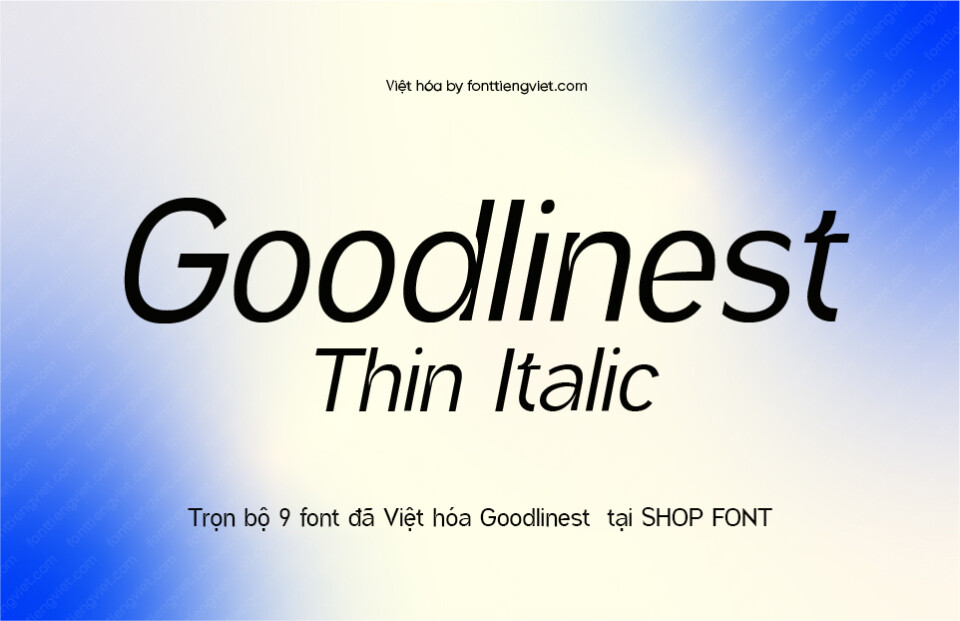
Font Việt hóa 1FTV VIP Goodlinest Thin Italic
Font Việt hóa 1FTV VIP Goodlinest Thin Italic: Đẳng cấp thiết kế thanh lịch và hiện đại
Giới thiệu về Font Việt hóa 1FTV VIP Goodlinest Thin Italic
Trong thế giới sáng tạo đồ họa ngày nay, việc lựa chọn bộ Font Miễn Phí chất lượng đóng vai trò then chốt giúp sản phẩm truyền thông trở nên chuyên nghiệp hơn. Font Việt hóa 1FTV VIP Goodlinest Thin Italic là một trong những đại diện tiêu biểu cho phong cách tinh tế và nhẹ nhàng. Đây là phiên bản được tối ưu hóa hoàn toàn cho ngôn ngữ tiếng Việt, giúp các nhà thiết kế không còn lo lắng về lỗi hiển thị dấu khi sử dụng các phông chữ ngoại nhập. Với đường nét mảnh mai kết hợp cùng độ nghiêng tinh tế, bộ phông này mang lại cảm giác bay bổng và sang trọng cho mọi khung hình.
Đặc điểm nổi bật của bộ font chữ VIP
Đúng như tên gọi của nó, 1FTV VIP Goodlinest Thin Italic sở hữu độ mảnh (Thin) vô cùng ấn tượng. Những nét chữ được gọt giũa tỉ mỉ, tạo nên sự thanh thoát nhưng vẫn đảm bảo tính dễ đọc. Phiên bản Italic mang đến sự chuyển động mượt mà, giúp văn bản không bị khô cứng mà trở nên có hồn hơn. Đặc biệt, quá trình Việt hóa đã được kiểm soát chặt chẽ để đảm bảo các ký tự có dấu như “ă”, “ê”, “ơ” hay dấu hỏi, dấu ngã được đặt ở vị trí cân đối, hài hòa với cấu trúc tổng thể của chữ cái gốc.
Ứng dụng thực tế của Font Việt hóa 1FTV VIP Goodlinest Thin Italic
Mỗi bộ phông chữ đều mang một ngôn ngữ riêng và Font Việt hóa 1FTV VIP Goodlinest Thin Italic thường được ưu tiên sử dụng trong các dự án đòi hỏi sự cao cấp. Đối với các bạn học sinh và giáo viên, bộ phông này cực kỳ phù hợp để làm tiêu đề bài thuyết trình PowerPoint, làm bìa tiểu luận hoặc thiết kế các tấm thiệp chúc mừng ý nghĩa. Sự thanh mảnh của nó giúp trang giấy không bị rối mắt, tạo không gian thoáng đãng cho bố cục thiết kế.
Sử dụng trong thiết kế thương hiệu và truyền thông
Không chỉ dừng lại ở môi trường học đường, bộ phông này còn là trợ thủ đắc lực cho các designer trong việc thiết kế logo, bao bì mỹ phẩm hoặc các ấn phẩm tạp chí thời trang. Nhờ tính thẩm mỹ cao, nó dễ dàng tạo nên sự kết nối cảm xúc với người xem. Khi kết hợp cùng các tông màu pastel hoặc màu trung tính, phông chữ sẽ phát huy tối đa vẻ đẹp quý phái của mình. Việc cài đặt cũng vô cùng đơn giản, tương thích tốt với các phần mềm phổ biến như Adobe Photoshop, Illustrator hay các ứng dụng thiết kế trực tuyến như Canva.
Cách tối ưu hóa trải nghiệm người dùng với font chữ đẹp
Để sử dụng Font Việt hóa 1FTV VIP Goodlinest Thin Italic hiệu quả nhất, bạn nên lưu ý về độ tương phản giữa màu chữ và màu nền. Do đặc tính nét mỏng, phông chữ này sẽ hiển thị tuyệt vời nhất trên các nền đơn sắc hoặc ảnh có độ chi tiết thấp. Tránh sử dụng quá nhiều hiệu ứng đổ bóng cầu kỳ vì có thể làm mất đi vẻ đẹp tự nhiên của các đường nét thanh mảnh. Hãy thử kết hợp nó với một phông chữ không chân (Sans-serif) dày hơn ở phần nội dung để tạo ra sự tương phản thị giác thú vị và chuyên nghiệp.
Lợi ích khi lựa chọn phông chữ đã Việt hóa
Sử dụng các bộ phông đã được Việt hóa kỹ lưỡng giúp tiết kiệm thời gian chỉnh sửa thủ công từng dấu chữ cái. Điều này cực kỳ quan trọng đối với những người mới bắt đầu làm quen với thiết kế đồ họa. Bạn có thể tự tin sáng tạo các nội dung tiếng Việt thuần túy mà vẫn giữ được tinh thần nguyên bản của tác giả bộ chữ Goodlinest. Đây chính là giải pháp tối ưu cho những ai đang tìm kiếm sự hoàn hảo trong từng chi tiết nhỏ nhất của văn bản.
Kết luận về bộ Font Việt hóa 1FTV VIP Goodlinest Thin Italic